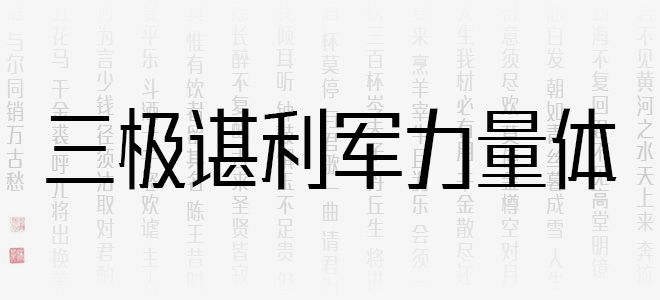
三極諶利軍力量體靈感來自于奧運(yùn)體育精神,筆畫撗細(xì)豎粗,整體字形方正棱角分明,結(jié)構(gòu)嚴(yán)謹(jǐn),布白均勻,撇、捺筆畫鏡像均勻?qū)ΨQ,字形充滿整個(gè)字面框,重心穩(wěn)定。適用于商業(yè)品牌的廣告、產(chǎn)品包裝設(shè)計(jì)、影視作品,界面設(shè)計(jì)等。